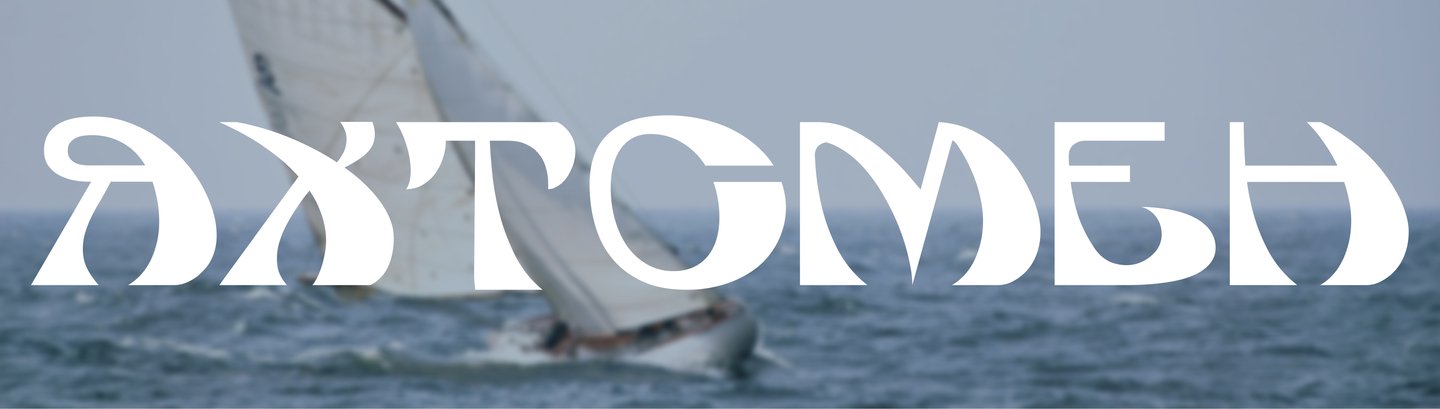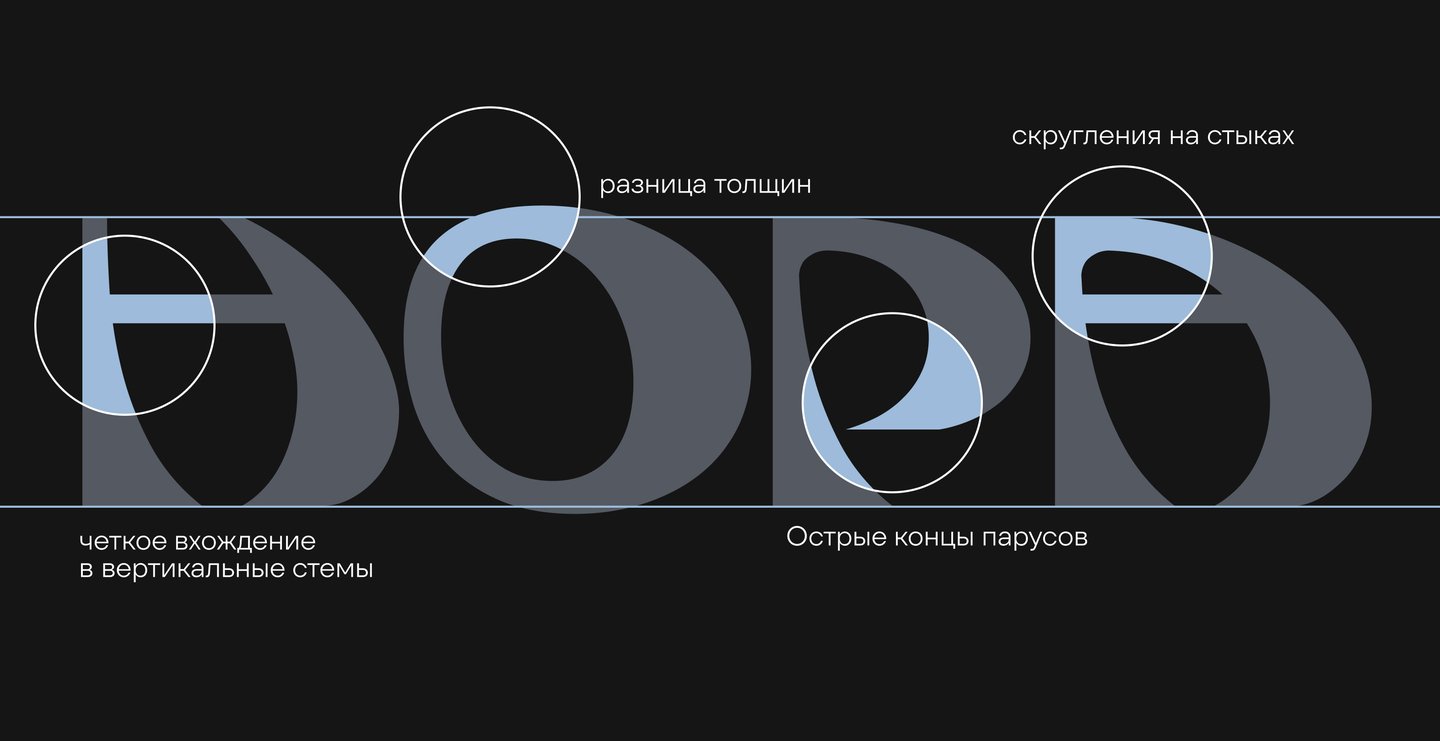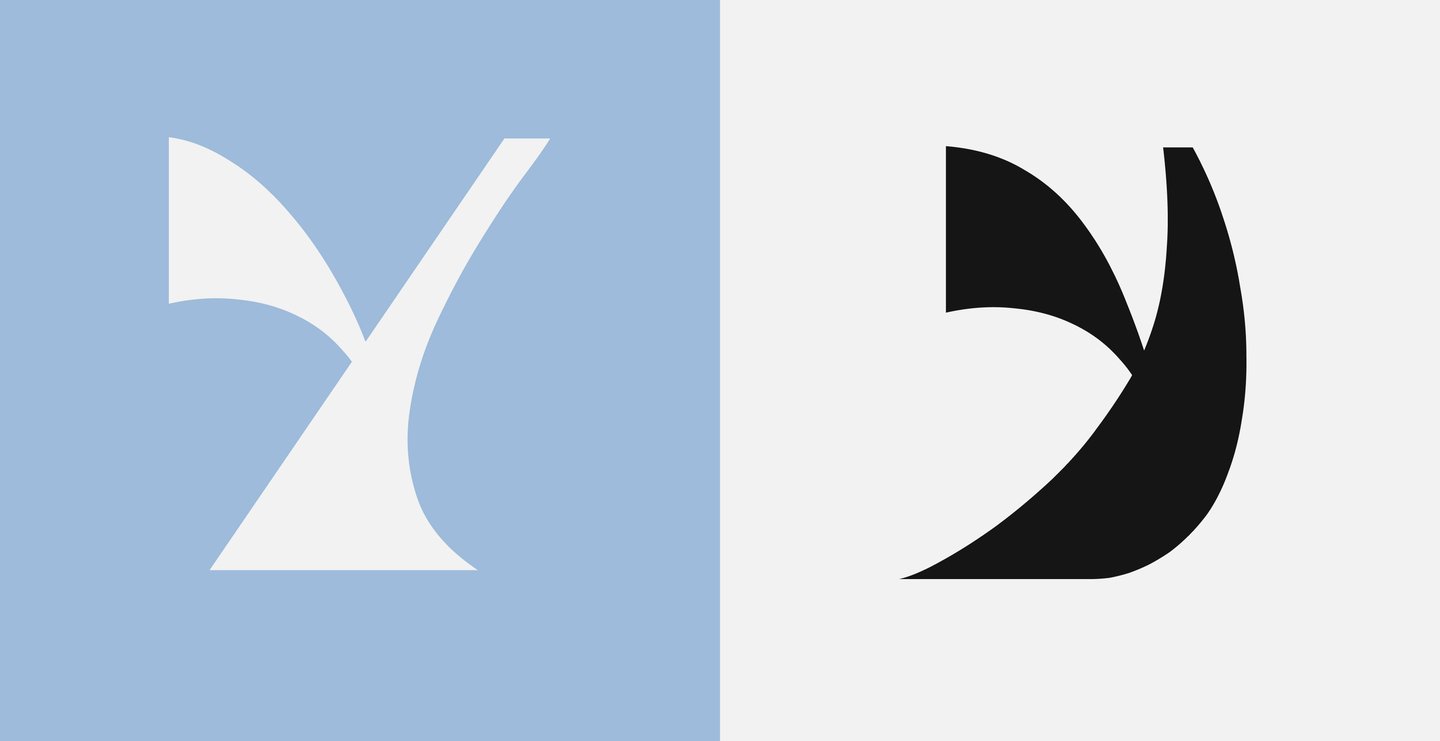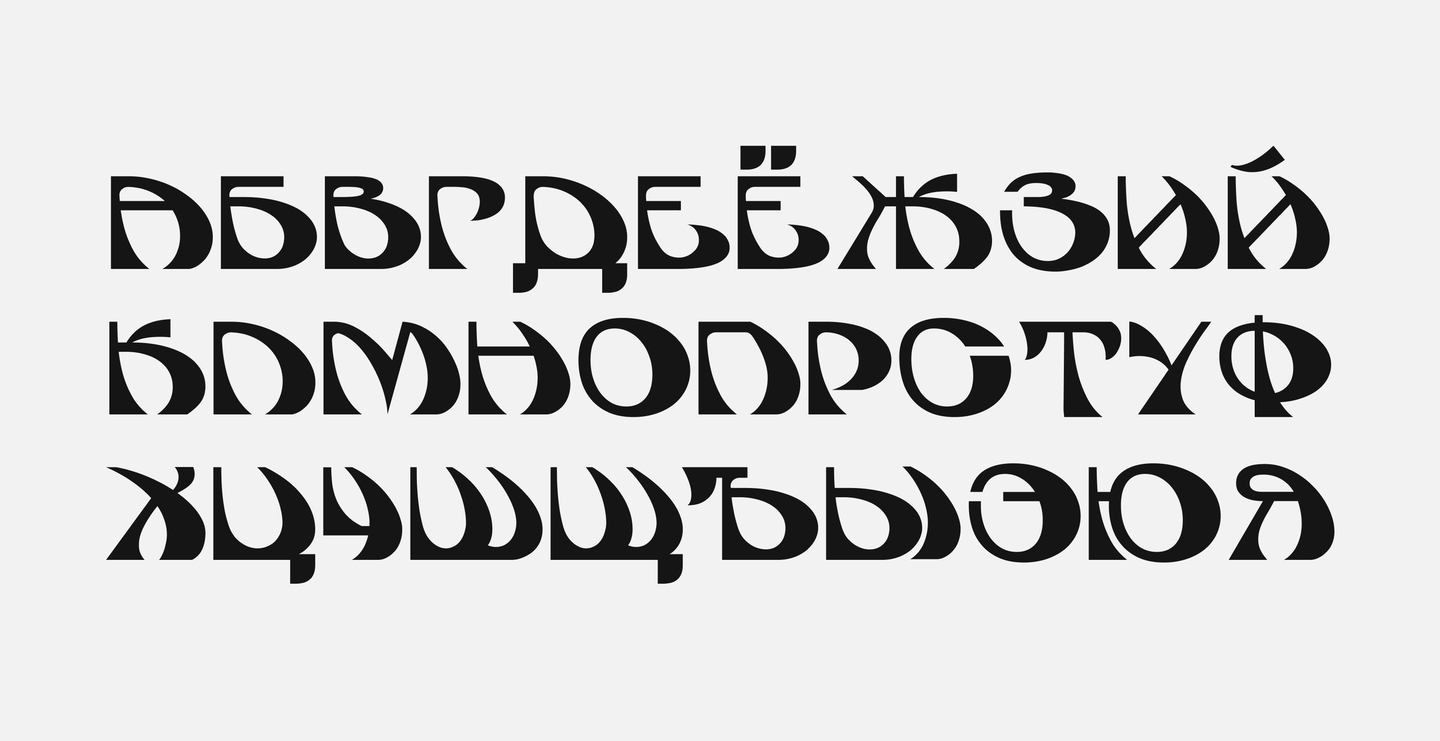
Декоративный акцидентный шрифт, вдохновлённый формой парусов и морской эстетикой
Шрифт переосмысляет силуэт паруса: формы букв повторяют линию натянутого и надутого ветром полотна, за счёт чего возникает ощущение объёма и плавного движения вперёд.